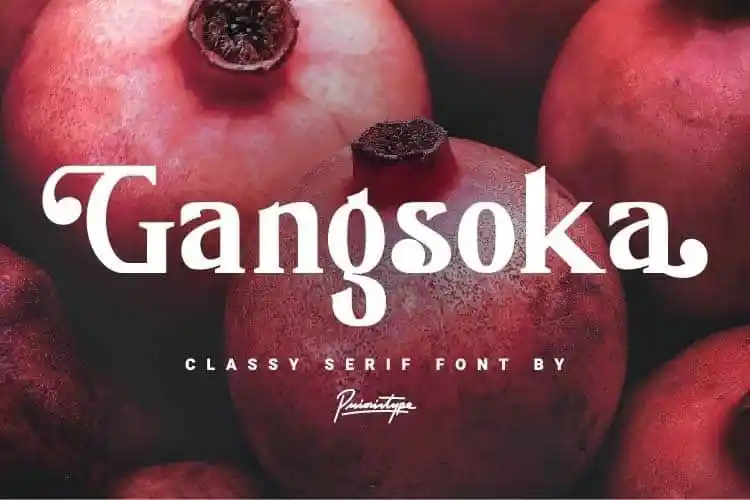
Gangsoka Serif Font
A Gangsoka Serif Font é uma moderna serif bold que adiciona elegância aos projetos digitais e impressos. Suas alternativas estilizadas e ligaturas unicamente a tornam ainda mais singular, permitindo sua utilização em uma ampla gama de aplicações. Esta fonte elegante é perfeita para criação de logomarcas, embalagens de alimentos, lojas de acessórios, roupas, itens criativos e muito mais. Não hesite em explorar os previsos, disponíveis no preview da Gangsoka Serif Font. Se você busca uma fonte única que se destaca das demais, esta pode ser a escolha perfeita para seu próximo projeto.